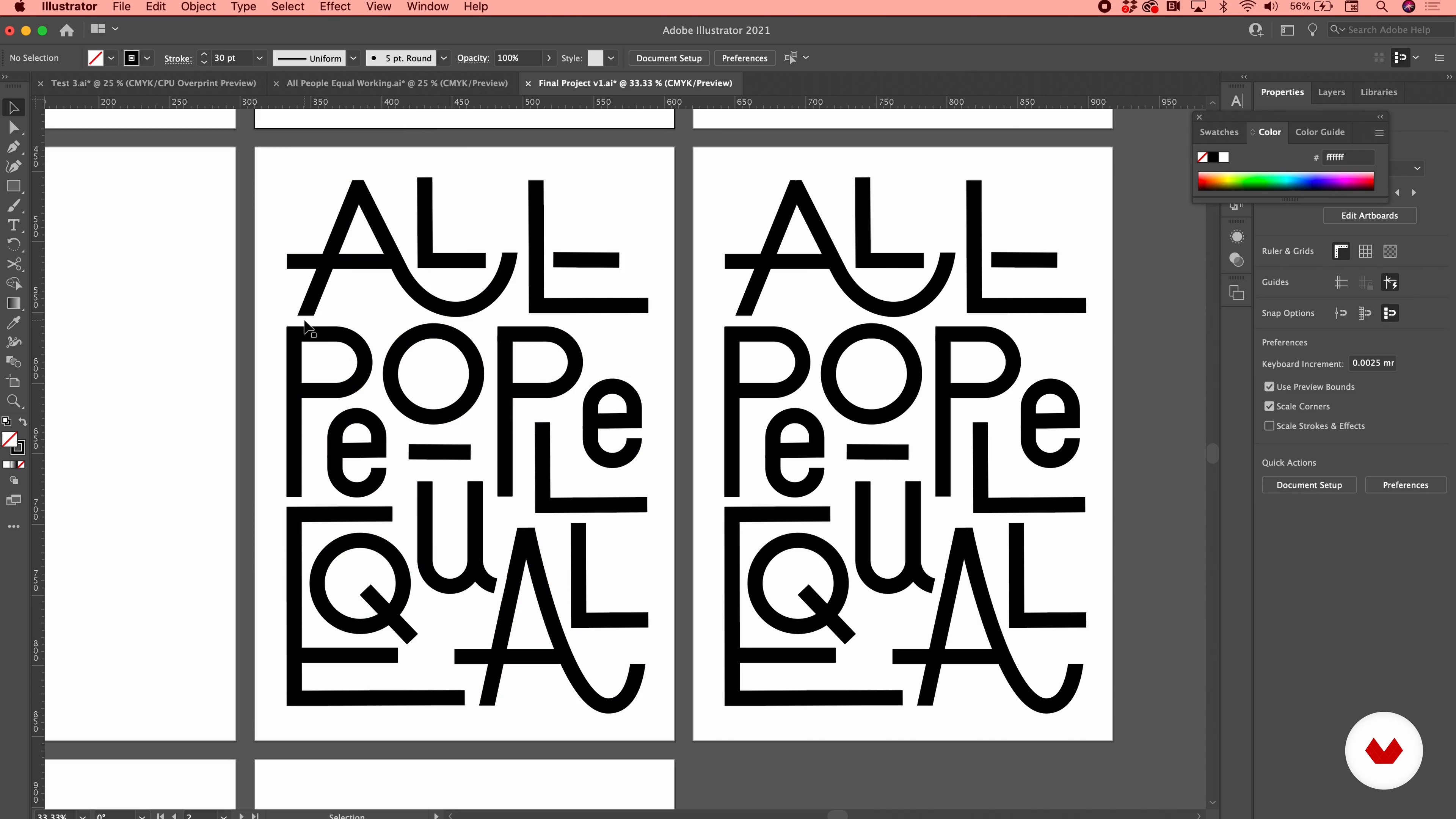
Illustrator : typographie ludique et communication efficace
Fabriquer les lettres
À propos de la leçon : Fabriquer les lettres
“Vous apprendrez à créer votre type en tant que vecteurs finaux. Ensuite, je vais vous donner des conseils pour essayer différentes mises en page en utilisant plusieurs plans de travail. Enfin, je vais vous apprendre à configurer vos plans de travail avec des marges et des guides pour vous aider à créer une pièce finie équilibrée. ”
Dans cette leçon, Dani Molyneux aborde le sujet : Fabriquer les lettres, qui fait partie du cours Domestika en ligne : Illustrator : typographie ludique et communication efficace. Découvrez les bases de la typographie pour créer des compositions frappantes qui exploitent pleinement le pouvoir des mots.
“Fabriquer les lettres Dans cette leçon, nous utiliserons les techniques que nous avons apprises pour créer des caractères, les développer et commencer à créer des lettres. Commençons. Maintenant, notre pièce type avance un peu. Je veux commencer à résoudre certains de ces problèmes d'espace. C'est un problème ici. Il y a un espace bizarre. Si vous ne savez pas quoi chercher, imprimez-le simplement... Je veux dire, regardez-le dans différentes couleurs et regardez où l'œil est attiré et si vous voulez que ce soit comme ça. Pour moi, je ne peux pas arrêter de regarder ce grand espace ici, don...”